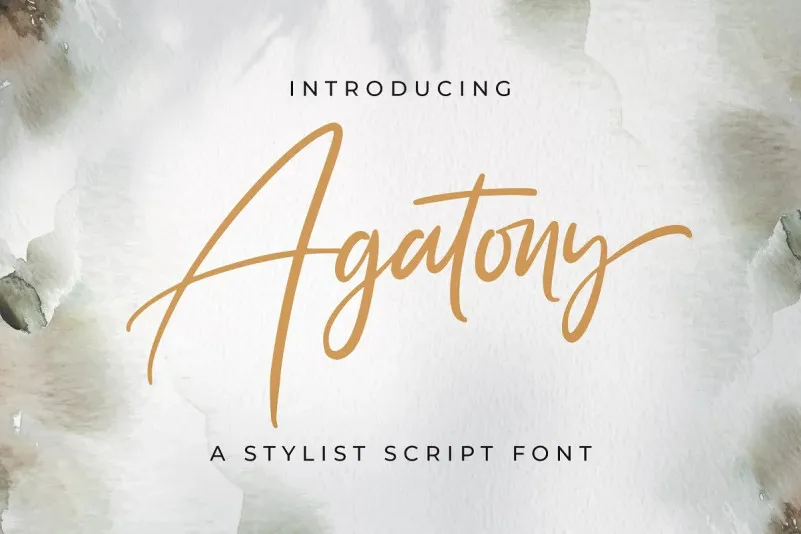
Agatony Script Font – Download Grátis
A Agatony Script Font é uma tipografia de script criada por StringLabs com traços contrastantes e caracteres divertidos. Desenvolvida para designers amadores e profissionais, ela oferece um equilíbrio perfeito entre beleza e simplicidade. As letras são belas e bem balanceadas o suficiente para combinar em uma variedade de projetos criativos. Experimente a Agatony Script Font no seu próximo projeto gráfico – você vai notar como ela dá vida às suas ideias mais originais. Esta fonte é perfeita tanto para criações simples quanto para designs elaborados, garantindo um toque único em seus trabalhos. Não hesite em adicionar a Agatony Script Font aos seus projetos e veja como ela eleva seu trabalho ao próximo nível.